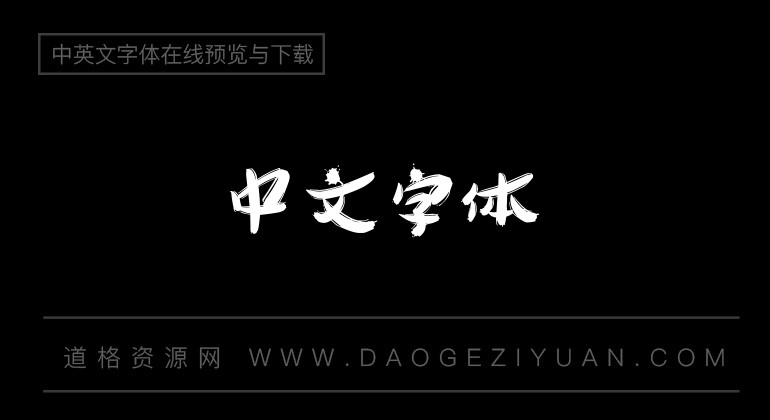
苏新诗毛糙体简
苏新诗毛糙体简是一款中国传统毛笔字体,它来源于清朝的苏轼的诗歌创作,受到诗人的影响而演变而来。它的特点是毛笔字体,笔画粗糙,笔画间隔较大,字体较大,笔画流畅,笔画细腻,字形端正,视觉上更加细腻。它很适合用于书法、插画、绘画等传统艺术创作。
苏新诗毛糙体简是一款非常不错的手写艺术字体,具有很好的视觉感,适合于文化类的宣传设计、商业类品牌的广告和产品包装设计以及个性化文字排版等较多场景。